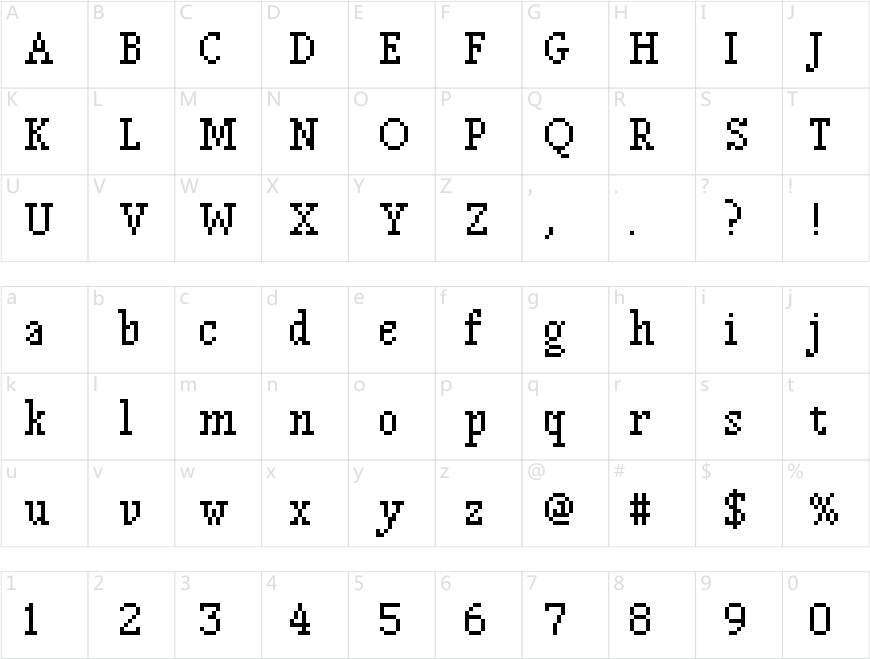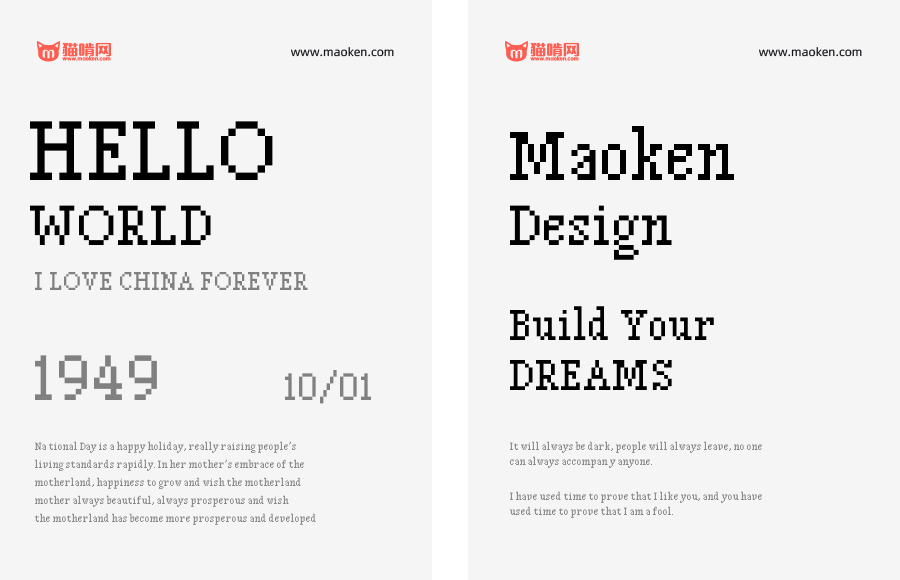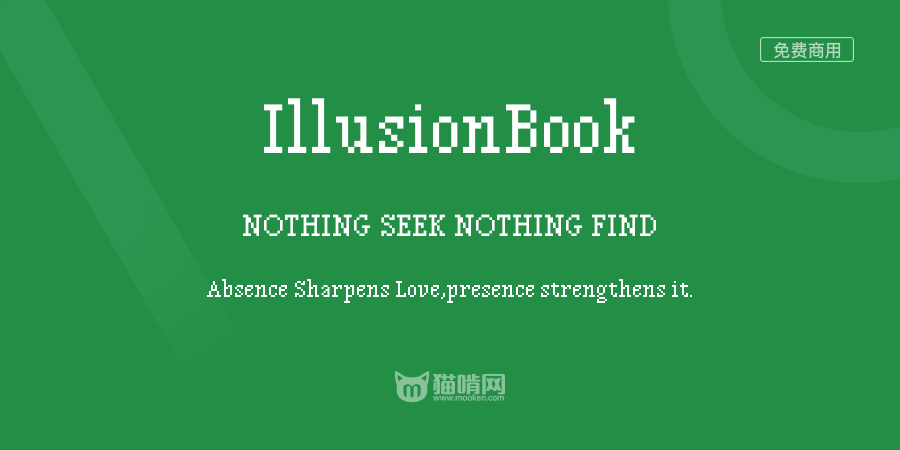
IllusionBook
字体作者:Steven Liu (中国大陆) 字体字重:1个
「幻象像素书体」是继幻象像素衬线体后,独立设计的第二款衬线风格的像素字体。经过半年多的设计与打磨后,完成了以西文为主的支持。目前其他例如中日韩的字符集仍在开发中。
设计
两者在风格上很相似,甚至有些字母的字形是完全一致的。因为它们的设计理念都是希望能够在像素风格上,展现衬线体所特有的优雅,同时还要有高可读性,适用于大段文本。
然而,这款字体最显著的变化便是缩小了字怀。小巧的字怀使文字的排列更加紧致,灰度更加均匀,同时不失节奏感。
字形也并未设计成等宽的样式,因为有些字母强行拉宽会显得十分拖沓;而有的强行压缩则又会拥挤不堪。在设计时大量参考了传统的旧式字体,例如罗马大写体,对每个大写字母的宽度进行了分类,并以此为依据进行设计。
在比例上,整套字体基于 12px 的尺寸进行设计。升部的高度为 9px,降部的高度为 3px。大写字母的高度被特意设计成比升部矮一个像素;而 6px 高的小写字母既不显得过于狭长,也不矮胖。
高级排版特性
虽然看上去是像素的,但并不是老旧的像素字体格式,所有的「像素」其实都是由矢量轮廓描摹出来的,除此之外,它还配备了丰富的高级排版武器,即 OpenType 特性。在专业的平面设计和排版软件(比如 Adobe InDesign 和 Illustrator)以及网页开发中,它能够让文字以更加灵活的方式呈现。
比如,按照西方排版惯例,自动将一些字母连写的合字(liga­ture)功能:
以及为了配合小写字母的旧式数字(old-style figures):
还有小型大写字母(small cap­itals):
技术指标
该字体的 UPM 值为 1200。若想取得最佳显示效果,字号应基于 12px 的大小进行整数倍的缩放。